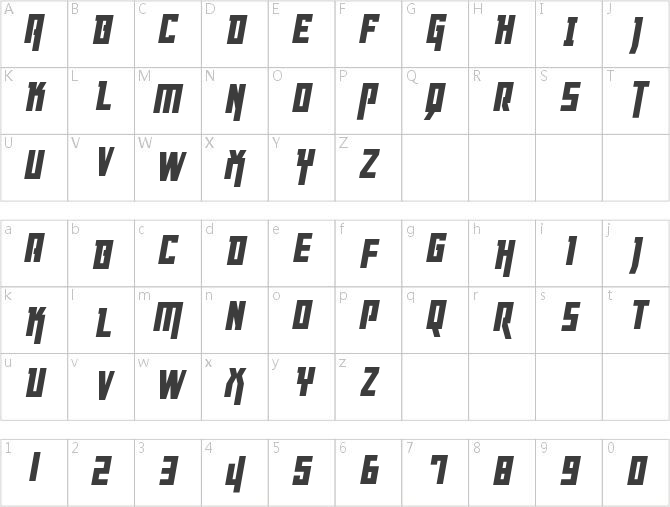
Danger Flight Condensed Italic 詳情頁
Danger Flight Condensed Italic
Danger Flight Condensed Italic介紹
Danger Flight Condensed Italic字體字庫是一款讓人賞心悅目、百看不厭的英文字體,適合各類廣告和產品包裝設計應用,字體大小0.02MB,格式為ttf字體,上傳用戶是17199970014,作者/版權方為未知